DynaFont年間ライセンス「DynaSmart V」
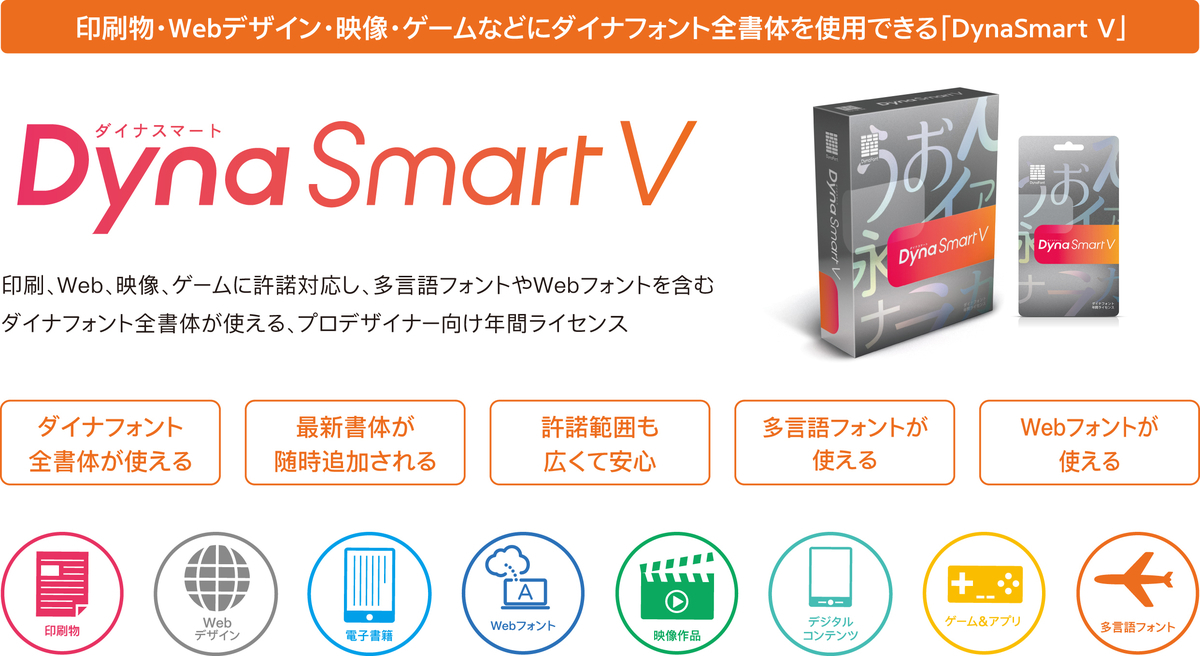
18種類の言語に対応した「金剛黒体」や「古籍五書体」「甲金文体」といったグッドデザイン賞受賞書体など国際的アワード受賞を含む、ダイナフォント全書体が使用可能な年間ライセンス。
アップグレードで話題の最新書体が随時追加となるほか、印刷物、映像、放送、電子書籍、ゲーム&アプリ、デジタルコンテンツ、Webデザインなど様々なコンテンツに許諾対応しており、全ダイナフォントを安心して使用できる。
また、多言語フォントやWebフォントクラウドサービス「DynaFont Online(DFO)」も利用できる。
DynaFont年間ライセンス「DynaSmart T」
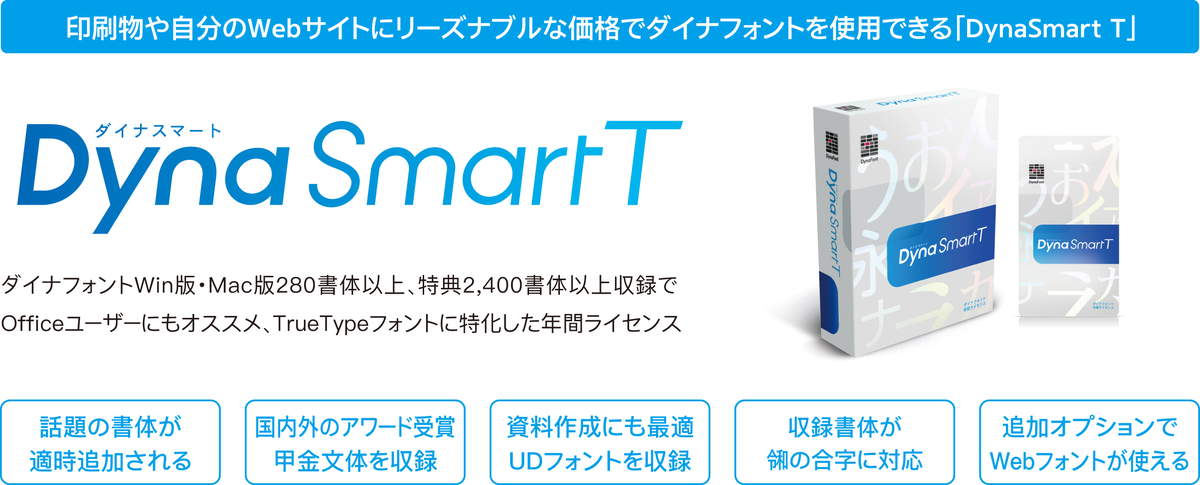
「DynaSmart T」は、スタンダードなゴシック体・明朝体から、老若男女問わず誰にでも読みやすいUDフォント(ユニバーサルデザインフォント)、楷書・行書・隷書などの毛筆系書体、バラエティに富んだ各デザイン書体、そして「古籍五書体」といったグッドデザイン賞受賞書体までダイナフォントTrueTypeフォントWin版・Mac版280書体以上、特典フォント2,400書体以上が使用可能な年間ライセンス。